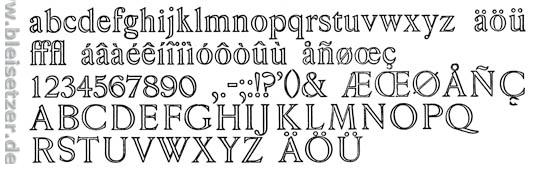
Kombinierbare Schriftschnitte
Also ich bin studienbedingt auf der Suche nach Beispielen für Fonts welche so angelegt sind das sich mehrere Schnitte z.B. verschiedenfarbig übereinander legen lassen. Da gibt es ganz einfache Beispiele wo z.B. ein Schnitt die Buchstaben ein anderer die Outlines dafür enthält.
Was ich jetzt suche sind aufwendigere Beispiele. Am liebsten wäre es mir wenn ihr gleich bilder posten könntet, aber auch die Namen der Fonts würden mir weiterhelfen.
Das ist ja schon mal ganz interessant.
So in diese Richtung geht meine Recherche, was mir noch ein bisschen fehlt
sind Schriften bei denen es noch einen dritten Schnitt gibt oder wo man
sagen kann das jeder Schnitt für sich ein interessanter Display-Font ist.
Ich hab das in einem früheren Schriftentwurf von mir schon mal probiert,
allerdings besitzen zwei von drei Schnitten keine vernünftige Lesbarkeit mehr.
Lichte Römische Antiqua
Schriftgießerei Genzsch & Heyse, Hamburg
Erstguß 1912
Hausschnitt
Hier ein Muster mit der mageren Version der Römischen Antiqua für einen 2-Farben-Druck.
Bei der Bello gibt solche zusammensetzbaren Schnitte für häufig benutzte Worte.
jedenfalls gibt es dort schriften mit 4 layern.
ansonsten fällt mir noch die house gothic ein, die habe n auch eine
menge dingbats die sich kombinieren lassen. ähnlich wie die sauna
dingbats von underware.
dann gibt es noch das buch 'neugierig' von johannes erler (factordesign)
dazu gibt es auch eine schrift mit schatten.
FF jigger
Neo Retro
FF Primary Stone (hat auch 4 layer)
CA Aircona
und ansonsten noch mein selbst ersteller font, name wird nicht verraten,
den ich hoffentlich bald mit etwas hilfe fertig bekommen werde.
dieser ist auch ein layer font und besteht jetzt schon aus 4 layern,
ein 5 und 6 sind geplant. :)
Das ist ja schon ne ganze Menge Input aber mal noch ne Frage.
Hat schon mal jemand darüber nachgedacht jedem einzelnem Layer ne komplett andere Formensprache zu geben?
So das keiner der einzelnen Schnitte die gleiche Funktion erfüllen könnte, aber alle zusammen wieder ein Gesamtbild ergeben.
Hat schon mal jemand darüber nachgedacht jedem einzelnem Layer ne komplett andere Formensprache zu geben?
So das keiner der einzelnen Schnitte die gleiche Funktion erfüllen könnte, aber alle zusammen wieder ein Gesamtbild ergeben.
Bei der oben erwähnten Quadrex ist doch genau das der Fall, oder?
Ja doch. Aber bei der Quadrex funktionieren die Schnitte mit den Einzelteilen nicht mehr als lesbare Schrift.
Also da gefällt mir meine Lichte Römische Antiqua immer noch am besten.
Die meisten von Euch gezeigten Muster haben doch überhaupt keinen praktischen Nährwert. Wo, bitte, kann man die einsetzen?
Tatsächlich.
Also aufm Mac gehts. Das ist übrigens genau so eine Schrift wie ich sie suche. Kennt jemand ähnliche?